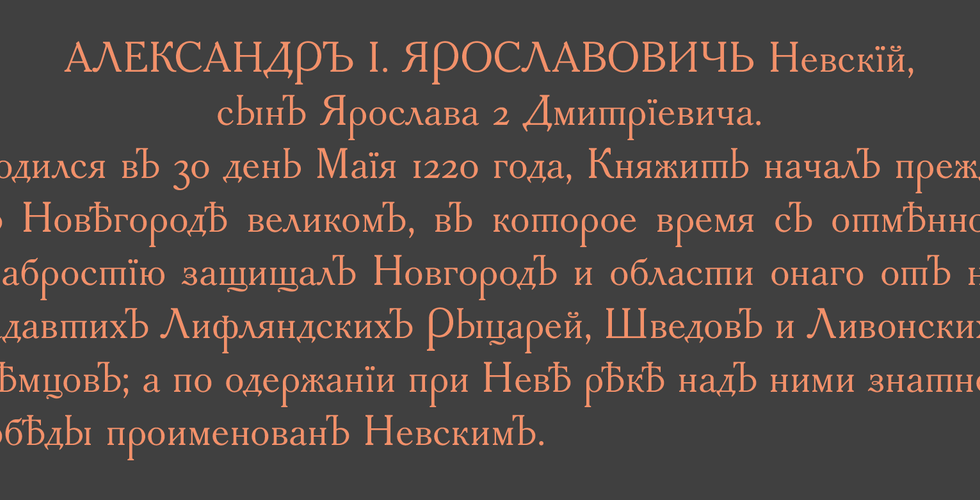
Шрифт Академический исторический/DXAkademischHistorisch
Выпущен шрифт DXAkademischHistorisch. Цифровая версия гарнитуры "Академическая историческая" словолитного заведения Г.Бертгольда, 1912(С.-Петербург). Текстовый шрифт с небольшим контрастом между штрихами.